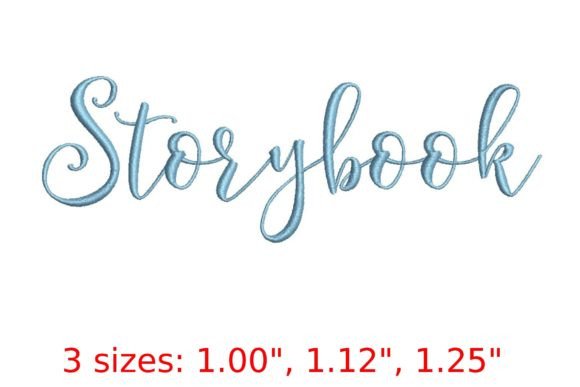
Storybook Embroidery Font
Storybook Embroidery Fontのような高品質の素材をお探しの場合、このプレミアムパッケージはクリエイティブなプロジェクトに素晴らしい選択です。
精密に作られたStorybook Embroidery Fontは、クリーンなベクター、滑らかなタイポグラフィ、そして安心のための商用ライセンスを提供します。
POD(オンデマンド印刷)製品、結婚式の招待状、またはソーシャルメディアのグラフィックを作成している場合でも、Storybook Embroidery Fontは理想的です。